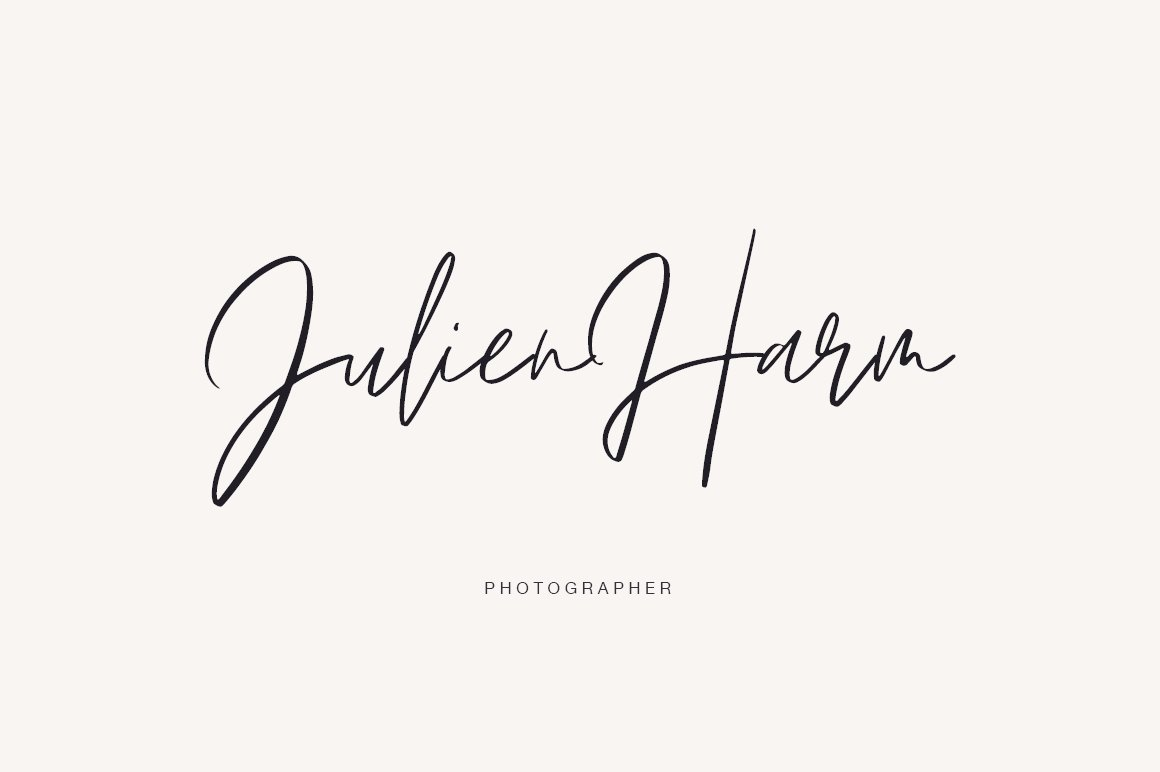
Emitha Script Font
Description de Emitha Script Font
Emitha Script Font comprend un ensemble complet de jolies lettres majuscules et minuscules, de symboles multilingues, de chiffres, de ponctuations et de ligatures. En outre, il comprend un large ensemble de Swashes et de Strokes. C’est tellement parfait pour les invitations, les monogrammes, etc.
Aperçu de la police Emitha Script